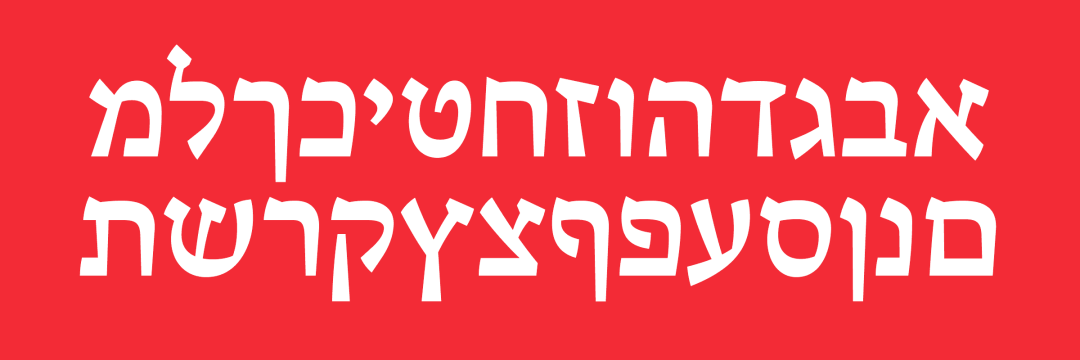
לכל פונט שמצטרף לקטלוג הפונטים שלנו יש את הסיפור הייחודי שלו. מרגע ההשקה, יש את הפונטים שזוכים להצלחה גדולה, אף מסחררת, בעוד שאחרים פחות ״נקלטים״, מסיבות שונות ומגוונות. מכיוון שאנחנו תמיד שואפים לשפר את קטלוג הפונטים שלנו – אחת לכמה זמן אנחנו מסדרים את כל הפונטים מחדש: יש פונטים שזוכים לגרסאות חדשות ואילו אחרים נאלצים לפנות את מקומם בקטלוג, משיקולי עריכה מגוונים, לטובת פונטים חדשים. ב־אאא תמיד נעדיף איכות על פני כמות. לֶס אִיז מוֹר!
הפונטים שעברו לפונטימונים
עומס
מעצבת ליה אופיר שם הפונט באנגלית Omes בקטלוג אאא 2011–2018
משקלים רגיל, בולד וסטנסיל
בדומה לאופן שבו ילדים סקרנים לומדים לכתוב אותיות דפוס לראשונה, הפונט עומס מתחקה בחופשיות אחר צורות השורש הבסיסיות של האות העברית. העבודה על הפונט נעשתה בזמן לימודיה של המעצבת בקורס בהנחיית מיכל סהר במחלקה לתקשורת חזותית בבצלאל.
מיקסטייפ
מעצב אברהם קורנפלד שם הפונט באנגלית Mixtape בקטלוג אאא 2013–2022
משקלים רגיל, בולד וחלול
פונט ידני, צעיר ונונשלנטי הכולל אותיות Uppercase ו־Lowercase באנגלית. הוא הושק בשנת 2013 בקטלוג אאא ובמשך השנים הפך להיות פופלארי ואהוב. בתחילת שנת 2022 הפונט עבר לקטלוג הפונטימונים וזכה לשדרוג, שכלל: שיפור קווי־האות, ניקוד מתוכנת ותוספת של 24 אייקונים חדשים. המשקל החלול נגנז ולא נכלל בגרסה החדשה (במקומו נוסף משקל האייקונים).
ספקטרום
מעצב רועי סטרדי שם הפונט באנגלית Spectrum בקטלוג אאא 2013–2018
משקלים בסיס (רגיל), שלד א׳, שלד ב׳, קו פנימי, צל תבליט, אאוטליין
פונט שכבות מודולרי בעל שבעה משקלים הניתנים לסידור בשכבות במגוון רחב של אפשרויות, כך שכל מעצב יוכל ליצור צורות אות חדשות בעצמו מתוך אינסוף האפשרויות. ניתן להשתמש בחלק מהמשקלים או בכולם, ולהרכיב אינסוף שילובים של שכבות בצבעים שונים.
רבקה באו
מעצב יוסף באו שם הפונט באנגלית Rivka Bau בקטלוג אאא 2013–2018
משקלים רגיל ובולד
אות קורסיבית, חיננית וזורמת שעוצבה על בסיס לטרינג שעיצב יוסף באו בשנות ה־60'. הפונט פותח בשנת 2013 על ידי אאא בשיתוף עם משפחת באו ונקרא על שמו של אשתו של יוסף. בשנת 2018 עבר הפונט באופן רשמי אל הפונטימונים, כאשר חלק מהכנסותיו הולכות לטובת שימור מורשתו של יוסף באו.
מוזיאון
מעצב ערן בכרך שם הפונט באנגלית Museum בקטלוג אאא 2012–2018
משקלים לייט, רגיל, בולד וכבד
פונט כיפי ומשוחרר בעל טעם לטיני מתוחכם, שנולד בעקבות הצורך לשלב אותיות עבריות עם אותיות לטיניות מסוג סלאב־סריף.
יידישקייט
שם הפונט באנגלית Yiddishkeit בקטלוג אאא 2016–2018
משקלים רגיל, בולד (חינמי) ושחור
פונט מחוספס שנולד מתוך כותרות עיתונים יידישאים משנות ה־40' שהודפסו בדפוס בֶּלֶט. הפונט הקלאסי שעליו יידישקייט מבוסס עוצב במאה ה־19 במזרח אירופה והוא וריאציה צרה של גופנים אשכנזיים־מרובעים מסגנון "דרוגו־וילנא".
פרשנדתא (לשעבר: פרשת השבוע)
מעצבת שני ברבר שם הפונט באנגלית Parasha בקטלוג אאא 2011–2012
משקלים לייט, רגיל ובולד
הפונט מתבסס על צורותיהן המיוחדות של אותיות כתב רש"י, אך משתמש בכלי מודרני – קו אחיד וממוחשב. המטרה בעיצוב הגופן הייתה ליצור חיבור גרפי טיפוגרפי, שתפקידו לחדש את הקשר בין עיצוב עדכני וחילוני לבין פנייה דתית מסורתית.
הפונט הופיע בקטלוג אאא למשך תקופה קצרה תחת השם ״פרשת השבוע״. בסוף שנת 2017 הפונט נבנה מחדש והושק בקטלוג הפונטימונים, תחת השם ״פרשנדתא״.
אייקונימונים (לשעבר: אלמוניקונים)
מעצב סטודיו אאא שם הפונט באנגלית Iconimonim בקטלוג אאא 2016–2018
משקלים סט אייקונים
על אודות
סט הולך וגדל של 400+ אייקונים שימושיים למעצב העברי והבין־לאומי, לדיגיטל ולפרינט. הסט נוצר בשנת 2016 על ידי אאא, אז הושק בשם ״אלמוניקונים״. בשנת 2018 עבר באופן רשמי אל הפונטימונים ושינה את שמו ל״אייקונימונים״. הסט כולל סמלים בנושאים: טכנולוגיה, טבע, תרבות עברית, יהדות, תחבורה, משרד, חיצים, וכמו כן סמלים של כל הרשתות החברתיות הנפוצות.
הפונטים שיצאו מקטלוג אאא
פואטי
מעצב ערן בכרך שם הפונט באנגלית Poeti בקטלוג אאא 2013–2018
משקלים לייט, רגיל ובולד
פונט בעל קו אינטליגנטי ורגיש המשלב בין חדש לישן ובין יציבות לזרימה. ההשראה לעיצובו לקוחה ממערכות שילוט ישנות משוק מחנה יהודה בירושלים ומגופני מקורות קלאסיים. הפונט עבר טיפול 'הינטינג' על ידי ניר ייני כדי להתאימו לתצוגה באתרי אינטרנט עבור טקסטים רצים.